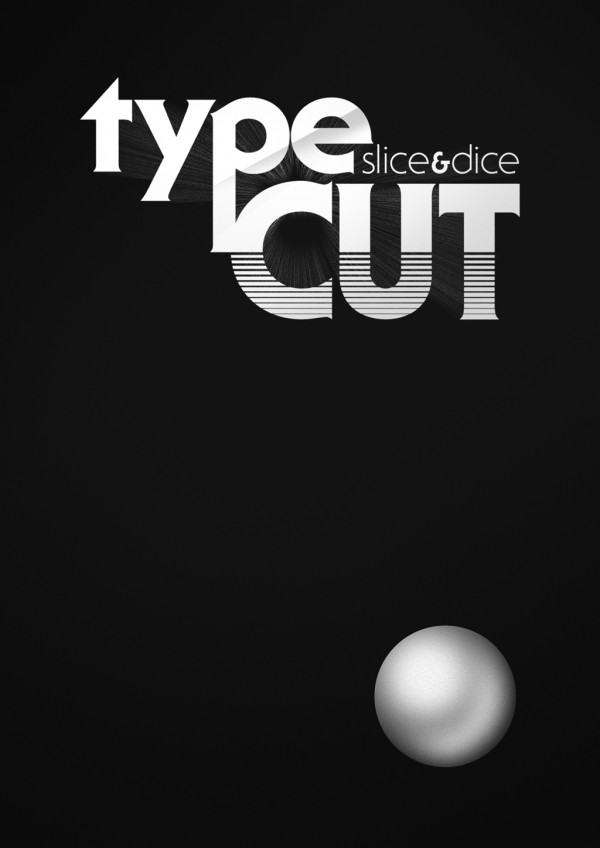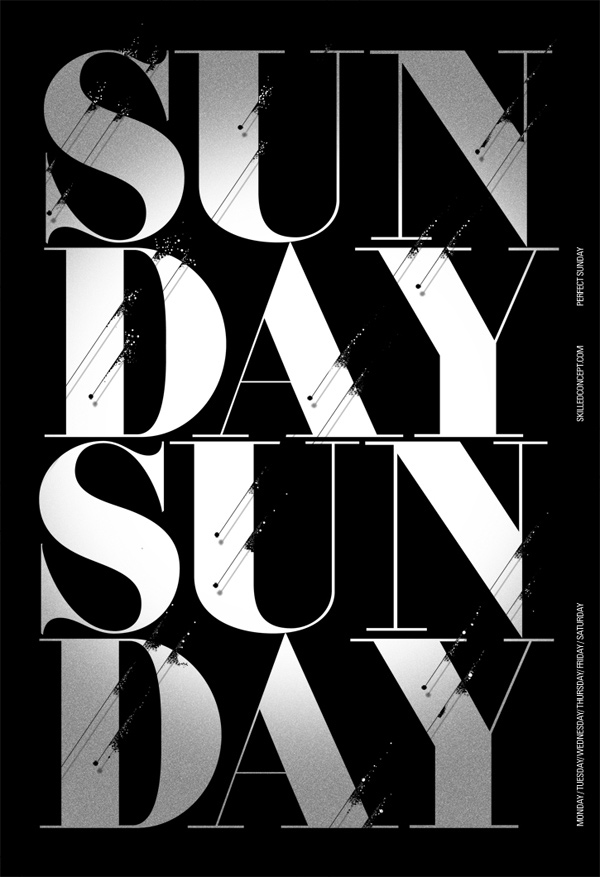
Typcut, tipografía experimental
Los trabajos mas experimentales de varios diseñadores en cuanto al campo tipografico y compositivo, muy buenas chispas creativas y demás que vale la pena checar de cerca, más desde su sitio que es este.